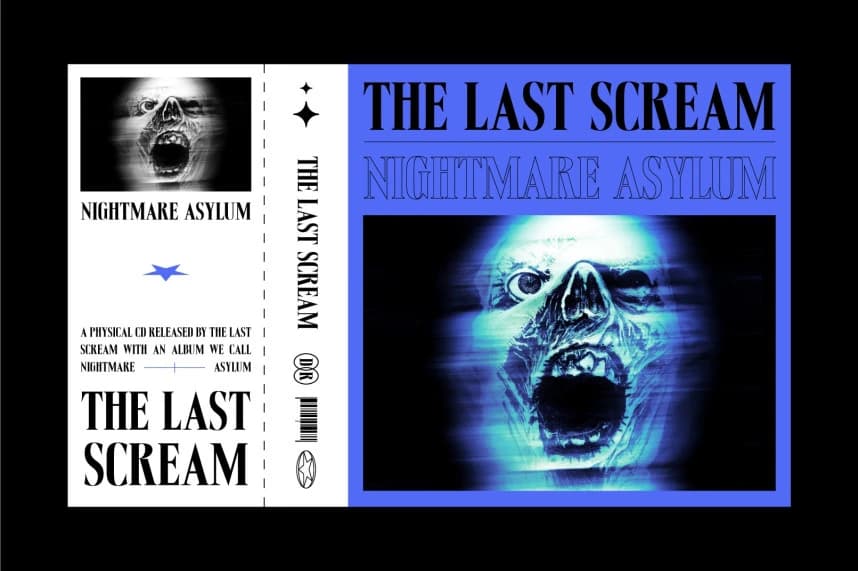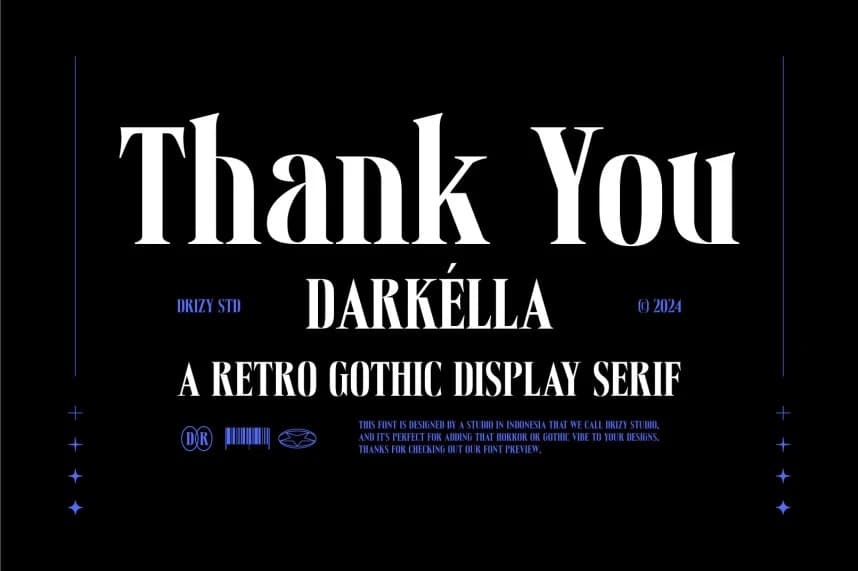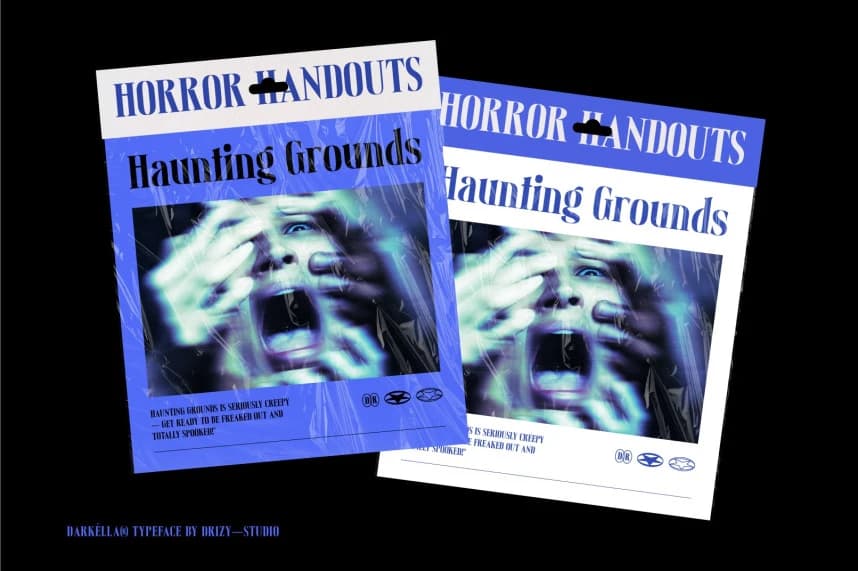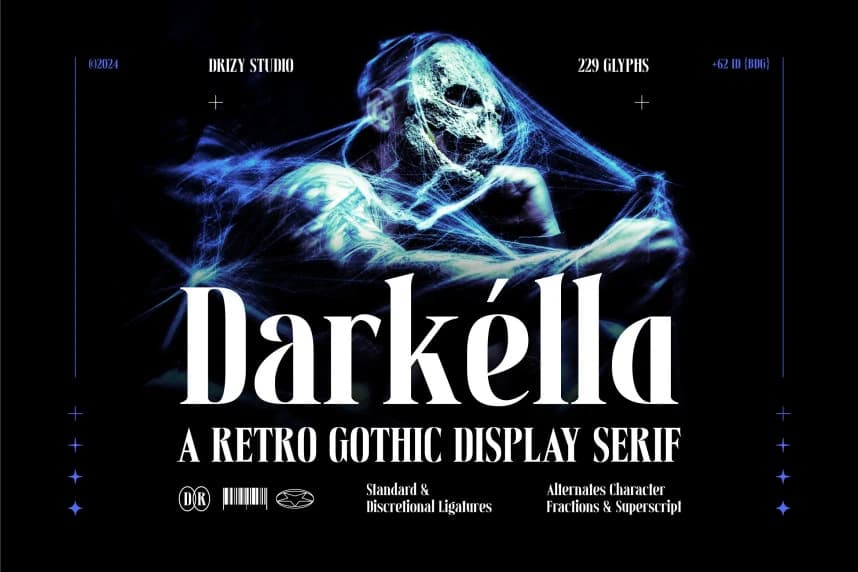
Darkella Font
Darkella Font, vintage zarafet ile karanlık cazibenin büyüleyici bir birleşimidir ve Cadılar Bayramı temalı projeleriniz için mükemmel bir seçimdir. Kalın ve süslü harf biçimleriyle Darkella, klasik gotik tipografinin ürkütücü özünü yakalar.
Darkella Font, vintage zarafet ile karanlık çekiciliğin büyüleyici bir karışımıdır ve Cadılar Bayramı temalı projeleriniz için mükemmel bir tercih sunar. Kalın ve süslü harf biçimleriyle Darkella, klasik gotik tipografinin ürkütücü özünü yakalar.